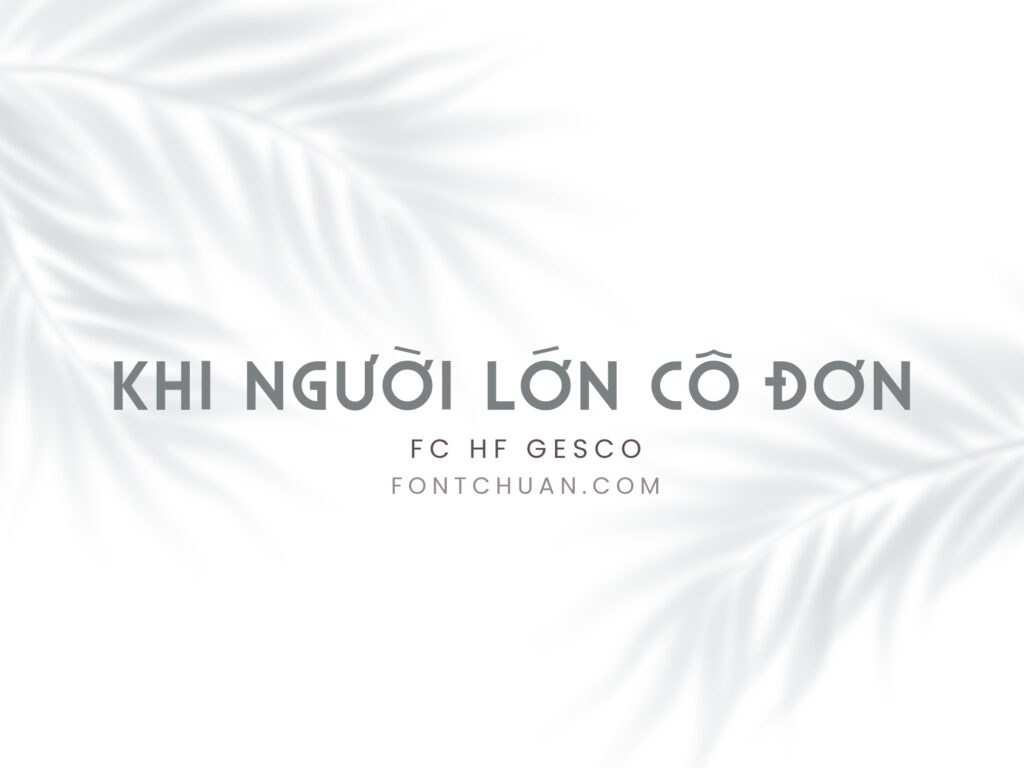
HF Gesco là một font chữ sans serif biến đổi với 3 trọng lượng: Light, Regular và Bold, được thiết kế bởi Nur Cholis Majid và phát hành vào khoảng năm 2024. Lấy cảm hứng từ các poster âm nhạc và bìa album thập niên 90, HF Gesco mang đến vẻ đẹp retro kết hợp với sự hiện đại, tạo nên sự độc đáo cho các thiết kế.
Với cấu trúc chữ hình học, các đường nét gọn gàng và sự đa dạng trong trọng lượng, HF Gesco phù hợp cho các thiết kế poster, tiêu đề, logo và các ấn phẩm quảng cáo khác. Đặc biệt, font này thích hợp cho dịp Tết, ngày lễ… và cho các ngành nghề như quảng cáo, thiết kế thiệp cưới và lĩnh vực thời trang, nơi cần sự kết hợp giữa thẩm mỹ cổ điển và hiện đại.